Tipografi yang relevan dengan tema desain christmas adalah yang memiliki style elegan tipis, dan sederhana. Jenis font seperti serif, script dan sans serif yang tipis akan relevan dengan tema desain. Kombinasi font yang elegan untuk desain konten christmas akan meningkatkan daya tarik visual dan relevan dengan tema desain.
Kebanyakan desain tema christmas akan memiliki kesan magis, elegan, menyenangkan dan tampil seperti perayaan. Tipografi bulat dan bebas akan cocok juga untuk tema desain christmas namun beberapa desain natal elegan akan lebih cocok dengan style font elegan. Untuk desain christmas kombinasikan font yang harmonis dan kontras tetapi juga mencerminkan tema desain dengan baik.
KOMBINASI FONT DESAIN CHRISTMAS
Dalam menciptakan desain natal elemen visual seperti tipografi harus dipilih dengan bijak akan menciptakan desain yang menarik. Kombinasi font yang kontras tetapi elegan akan meningkatkan daya tarik visual desain. Berikut beberapa kombinasi font untuk desain konten christmas yang elegan:
Kombinasi Font Kage dan Benedict
Font serif modern yang memiliki gaya huruf bersih dan elegan akan cocok untuk digunakan pada desain christmas. Jenis font serif harus dikombinasikan dengan font yang kontras seperti font script latin. Kombinasi font akan menciptakan desain christmas yang elegan dan menarik perhatian.
Font kage dan benedict tersebut terlihat kontras yang menarik dan jelas karena mengkombinasikan dua jenis font yang berbeda. Garis-garis huruf dalam font tersebut terlihat elegan sementara font script memiliki gaya huruf yang seperti tulisan tangan. Font serif memiliki garis lebih tebal dengan sudut yang tajam, cukup kontras dengan font script tampil lebih alami dan tidak kaku.
Kombinasi Font Singel dan Westonia
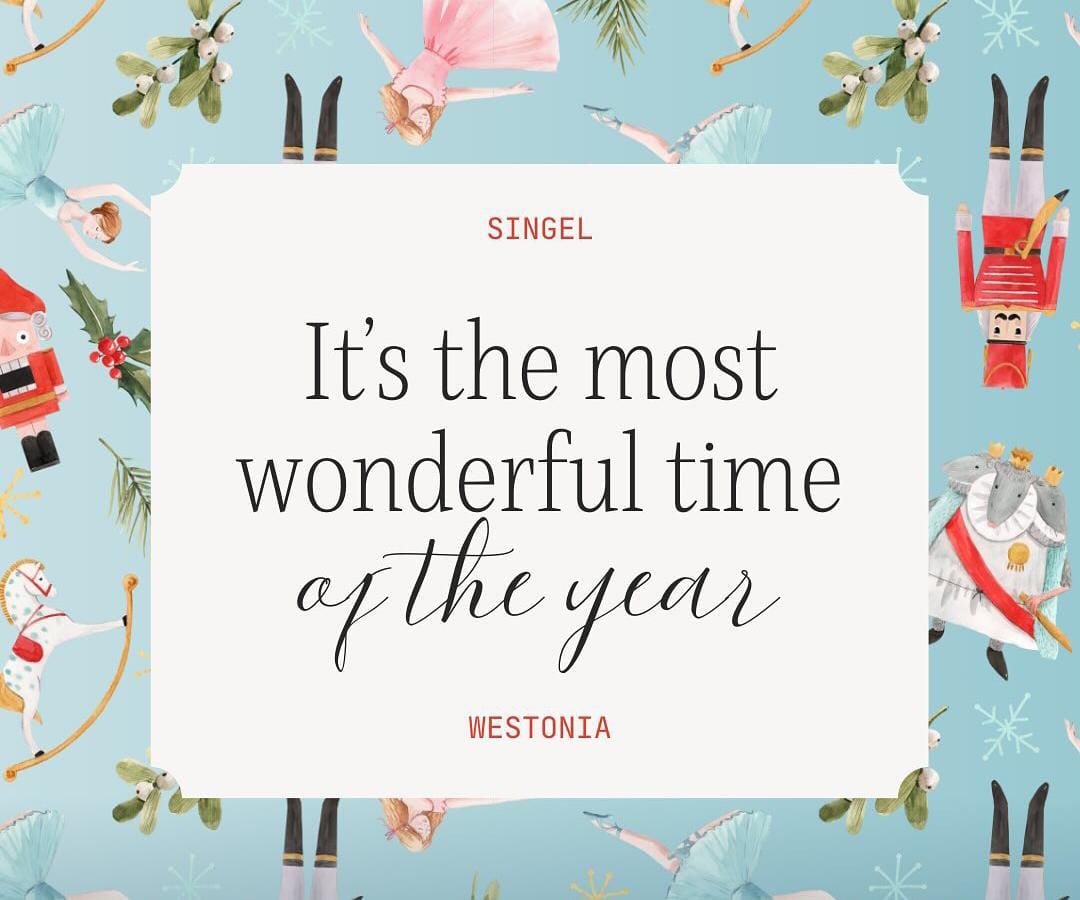
Berbeda dengan sebelumnya font serif dalam kombinasi tersebut tidak terlalu tebal dan tajam. Untuk desain christmas font serif yang tipis ini akan menciptakan desain yang elegan dan berkesan mewah. Font serif memiliki style huruf yang bersih dan mudah dibaca sehingga akan fleksibel dalam berbagai kebutuhan.
Font serif tersebut dikombinasikan dengan font script yang tipis dan memiliki huruf latin. Gaya font script terlihat lebih elegan dan tampil feminim, cocok untuk desain natal yang berkesan mewah. Kombinasi font yang kontras tersebut akan cocok digunakan untuk desain kemasan premium natal atau kartu ucapan natal.
Kombinasi Font Helsa Display dan Themysion
Banyak desain christmas yang mengkombinasikan font tipis dan tipis agar menciptakan visual yang minimalis. Untuk meningkatkan kontras dan hirarki visual, biasanya akan menggunakan ukuran teks yang besar atau jenis font kapital. Kombinasi font desain christmas tersebut menggunakan font serif kapital dan font script latin.
Meski sama-sama memiliki gaya huruf tipis tetapi ukuran teks pada font serif dapat dibuat lebih besar agar kontras. Selain itu gaya font tersebut memiliki jenis font kapital semua sehingga tampil lebih menonjol. Kombinasi tipografi kapital dan serif tipis terlihat kontras dan harmonis untuk menciptakan kesan elegan dan mewah.
Kombinasi Font Boston Angel dan Moontime
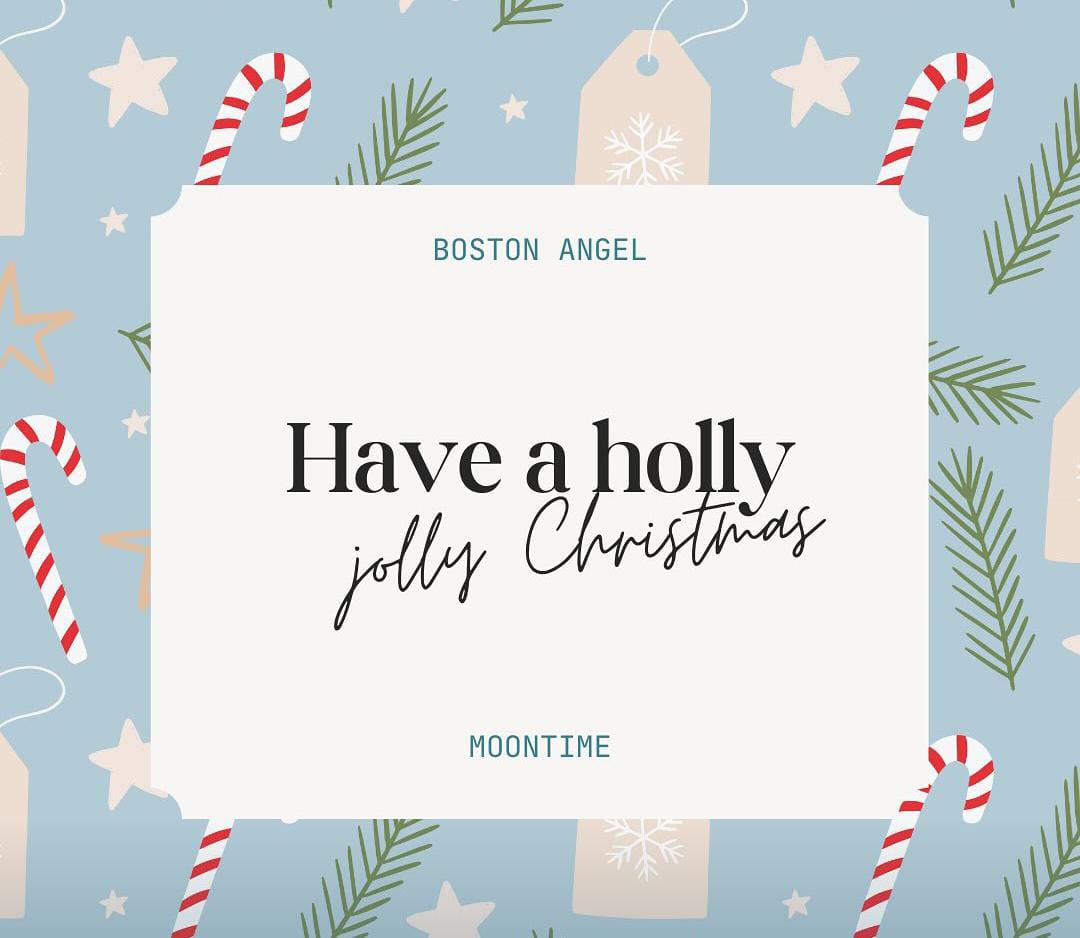
Jenis font serif modern termasuk banyak digunakan untuk tema desain christmas karena menciptakan kesan elegan. Desain christmas dengan style font serif modern yang elegan dan halus akan efektif menciptakan kesan elegan. Font serif modern tersebut memiliki garis huruf tebal dengan sudut tajam dan huruf yang bersih.
Font tersebut dikombinasikan dengan font script tipis yang bergaya alami dan sederhana. Kombinasi font terlihat kontras karena kegagalan huruf yang berbeda dan gaya huruf yang juga berbeda. Meski begitu kombinasi menciptakan kesan elegan dan cocok untuk desain konten tema natal.
CIRI TIPOGRAFI DESAIN CHRISTMAS
Setiap tema desain memiliki pesan dan kesan yang ingin diciptakan, untuk itu elemen visual seperti tipografi juga berbeda. Dalam tema desain natal, font yang digunakan harus mencerminkan suasana dan kesan natal. Secara umum tipografi natal akan memiliki gaya font seperti:
Menggunakan Font Elegan
Desain grafis natal sering menggunakan dekorasi pesta natal yang terlihat meriah, penuh warna dan elemen-elemen perayaan yang menarik. Pesta natal seringkali memiliki tampilan lebih elegan dan magis, untuk itu akan cocok menggunakan gaya font elegan. Jenis font elegan seperti serif modern tipis, sans serif elegan tipis dan script latin yang tipis akan cocok.
Terkadang gaya font handwritten yang elegan juga bisa menciptakan kesan elegan dan menyenangkan. Bahkan jika menggunakan lebih dari satu jenis font, kombinasi font desain christmas harus sama elegan. Font elegan christmas juga seringkali memiliki serif panjang, melengkung dan dekorasi elemen natal.
Memiliki Dekorasi Tipografi Menarik
Selain gaya font yang bersih, beberapa desain tema natal menggunakan font yang unik dan nyentrik. Font akan memiliki dekorasi elemen natal seperti lampu natal, pohon natal hingga dekorasi bintang. Jenis font display dengan dekorasi elemen gambar yang menarik akan membuat tipografi mencerminkan tema desain dengan baik.
Desain grafis tema christmas biasanya akan tampil meriah dan terkadang mewah dengan menggunakan elemen visual yang menarik. Termasuk juga menggunakan kombinasi font yang sesuai dengan kesan dan citra desain natal. Kombinasi font untuk desain natal kebanyakan akan memiliki ciri tipografi yang elegan, tipis, sederhana dan menciptakan kesan mewah. Pilih beberapa kombinasi tersebut untuk berbagai desain tema natal yang menarik perhatian.